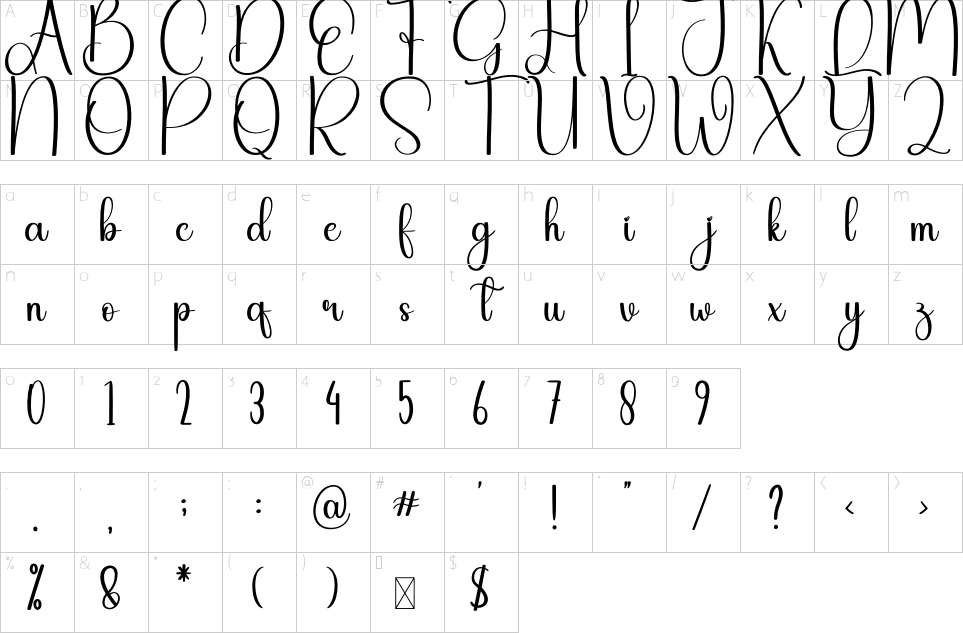
A Darling Font é uma elegante fonte gráfica gratuita que combina simplicidade com modernidade. Desenhada por um talentoso designer não mencionado neste caso, ela foi projetada para fornecer um visual atraente e único às suas criações digitais. Com seu design minimalista, a Darling Font é perfeita para uso em materiais impressos ou online, desde logotipos até textos de e-mail. Seu download já ultrapassou 407 vezes, demonstrando o quanto esta font é apreciada por criativos de todo o mundo. Experimente ela hoje e dê um toque especial à sua marca digital.